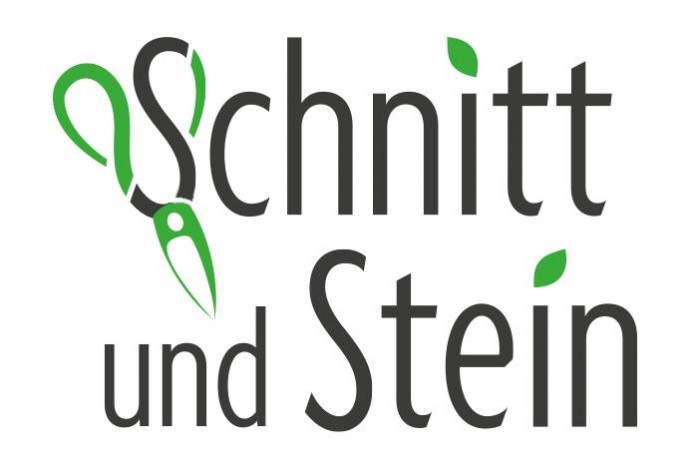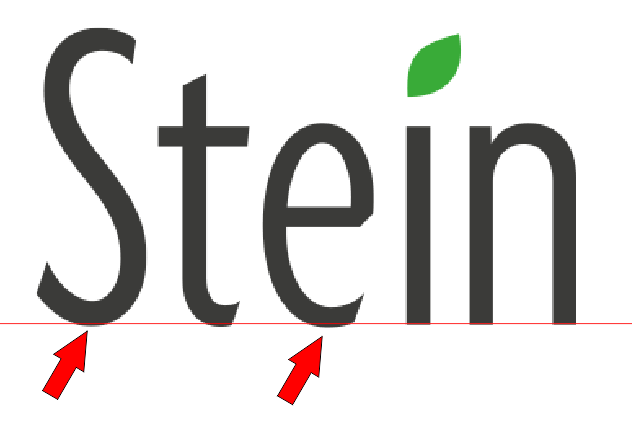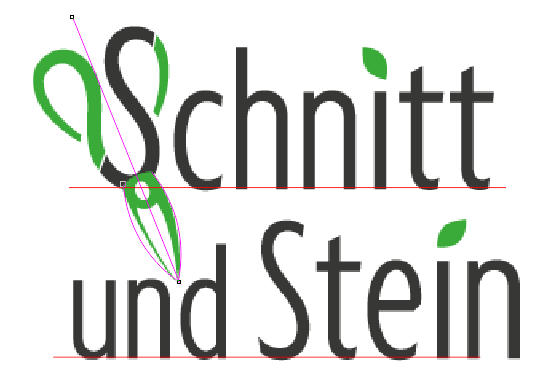
Hilfe bei Logoentwicklung
Das ist sehr viel besser!  :nicken:
Jetzt würde ich noch Kleinigkeiten optimieren:
- Die Schere noch etwas verkleinern, denn die Strichstärke des S ist immer noch größer als die der Buchstaben in »chnitt«und wirkt dadurch leicht irritierend – als könnte es ein Fehler sein. Alternativ könntest Du die restlichen Buchstaben fetter setzen, sodass sie in der Strichstärke auf das Scheren-S abgepasst werden.
- Gleiches gilt für das »und «. Es ist nur leicht kleiner als der Rest, aber es wirkt nicht gewollt. Ich würde dem »und« entweder die gleiche Strichstärke wie den Buchstaben der übrigen Worte geben (also dicker) i oder ich würde das »und« noch etwas verkleinern und ihm dann vielleicht sogar zusätzlich einen leichteren Schriftschnitt verpassen.
- Die weißen Lücken im Scherengriff würde ich noch größer machen – analog zu den Lücken der Endstücke des S
Wichtig ist, dass alle Bestandteile Deines Logos gewollt aussehen – mit Bedacht gewählt und absichtsvoll umgesetzt.
Die Schere sieht insgesamt immer noch »wackelig« und nicht sauber konstruiert aus.
Ist das obere S in der Schere größer als bei »Stein«? Und ganz identisch scheint es auch in der Form nicht zu sein. Aah Kathrin hatte das eben auch schon angemerkt.
Außerdem scheint mir das Klingenpaar nicht symmetrisch konstruiert zu sein.
Ich habe noch einmal in deinem Logo herumgekritzelt :-)
So richtig symmetrisch ist die Schere nund eben doch nicht.
Zum einen habe ich den Bogen in der oberen Klinge einmal um die Achse Drehgelenk - Scherenspitze gespiegei, ich würde hier für beide Seiten der Klinge den gleichen Bogen, jedoch wohl eher ein Mittelding der beiden Bögen verwenden, und dann sollte die Symmetrieachse eben auch sich mit der der Griffe decken. Diese Schere hat noch immer einen Knick.
Dann sorgt das aufgelegte Gewerbe der Schere noch immer dafür, dass das S in der Schere optisxch einen Tick höher erscheint, als "chere". Hierzu habe ich einmal die Grundlinie der Schrift eingezeichnet, um zu zeigen, wie runde Buchstaben, um optisch auf gleicher Höhe zu wirken, einen Hauch unter die Grundlinie hängen. Das ist bei allen Schriften so. Gut möglich, dass es bei dem S in der Schere auch der Fall wäre, wäre sie nicht durch das grüne Gelenk uberdeckt. Dieses hebt aber eben den Effekt wieder auf, und drückt das S etwas nach oben. ich würde daher die Schere um etwa 20% der S-Strichstärke nach unten schieben.
Und dann würde ich mal versuchen, das S aus der Schere zusätzlich komplett zu extrahieren und an Stelle des S von Stein zu verwenden, eventuell sogar den ganzen Text in Kurven zu konvertieren, und c und e an die Anschrägungen des Scheren-S anpassen. Die Schrift hat ja gerade bei den unteren Bogenenden quasi einen negativen Winkel, der hier eine scharfe Spitze erzeugt, während in der Sxchere sas S einen eher positiven Winkel, der die Spitze stumpfer macht enthält. Das sollte sich an c und e auch leicht machen lassen. In Logos kann man ja gern mal an Schriften etwas zupfen.
Und auch da bin ich mit meinen Vorrednern auf Linie, das "und" könnte ein wenig kleiner, damit man die bewusste Entscheidung für einen kleineren Schriftgrad deutlicher bemerkt.
ich habe nun einige Änderungen gemacht:
1. Schneide der Schere neu und symmetrisch konstruiert
2. Ganze Schere verkleinert, so dass das Scheren-S zu "chnitt" passt
3. Scheren-S unten bei Stein eingefügt
4. Untere Enden von c,e,t angeschrägt wie auch beim unteren Ende des Scheren-S (tolle Idee)
5. "und" verkleinert
6. Zwischenräume bei Schere (Trenner von Grün zu Grau) vergrößert
Anmerkung:
Ich habe die Klinge zwar symmetrisch konstruiert, dann aber etwas im Uhrzeigersinn gedreht, da die perfekte Symmetrie asymmetrisch wirkte!
Ich bin noch nicht zufrieden mit dem "S" von Stein, es wirkt mir zu Fett und groß
(oder bilde ich mir das ein)
Anbei einmal "alt" und "neu" im Vergleich:
Hey, für mich kommts jetzt gut. Aber sei ehrlich, du hast die Klingen nicht im Uhrzeigersinn, sondern genau anderherum gedreht?
Egal, es ist ja oft so, dass manches ein wenig Schief sein muss, um gerade auszusehen, denkt man nur an den Randausgleich beim Satz oder eben den Höhenausgleich bei runden Buchstaben, die eben ein wenig unter die Grundlinie ragen, bzw oben über die Versal bzw. x-Höhe hinausragen müssen.
Und genau da habe ich noch einen ganz winzigen Kritikpunkt, das Stein-S erschjeint optisch noch einen Mäusepfurtz zu hoch. Ich habe mal wieder die Grundlinie eingefügt (nutze Hilfslinien!) und siehe da, es hängt zwar einen Hauch unter die Grundlinie, aber eben noch weniger als das kleine e. Und gerade Großbuchstaben dürfen sogar eher ein wenig mehr nach Unten lugen. In deiner Auflösung hier, so etwa 1 - 2 Pixel. Nimm dir mal ein paar verschiedene Satzschriften, schreibe etwas Text aus unten gerade auf der Grundlinie stehenden Buchstaben, wie i und n in Stein und den gerundeten Buchstaben, wie O S, U, e, o, c, und ziehe die da mal eine Waagerechte, wie in meiner kleinen Grafik.
Das S der Schere steht mir im Vergleich zu den andern Buchstaben-Abständen ein wenig zu weit vom c weg. Je nach Gusto sollte man an einer der verfügbaren Schrauben noch mal drehen, finde ich.
Bin ich eigentlich der einzige, den stört, daß die Klingen der Schere mit dem Griff keine funktionale Einheit bilden?
Die Schere ist nur so lackiert und funktioniert schon … ;-)
Vielleicht ist es eine Taschenschere und man kann die Klingen um die Achse des Niets nach hinten über den Griff wegklappen. Das ist jedenfalls der Film, der in meinem Hinterkopf läuft, wenn ich draufschaue.